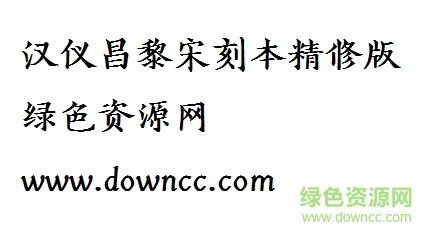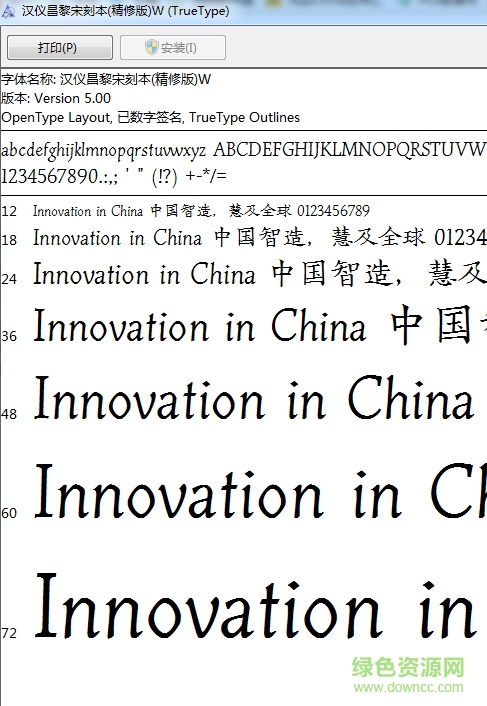
漢儀昌黎宋刻本精修版字體
漢儀昌黎宋刻本精修版字體是一款古典穩(wěn)重的漢儀字體軟件,宋刻本筆畫自然如流水,筆觸情節(jié)不多不少切好到位,整體效果賞心悅目,喜歡就到綠色資源網(wǎng)下載安裝吧!
漢儀昌黎宋刻本精修版保留其“神”意,字形規(guī)正中又略顯寬扁,筆畫縱橫清晰,結(jié)構(gòu)明朗疏正,工整嚴(yán)謹(jǐn)中又不失自然天趣。雖為刻本,但個別筆畫還留有斷筆和牽絲,保留了書法行筆的韻味,古意盎然。
漢儀昌黎宋刻本精修版
漢儀昌黎宋刻本,復(fù)刻于南宋時(shí)期廖瑩中和世彩堂學(xué)院所刻的《昌黎先生集》,此木刻本的木板剪切質(zhì)量上乘,紙張有光澤,光滑的墨水和其書法風(fēng)格,完好無損地流傳至今。